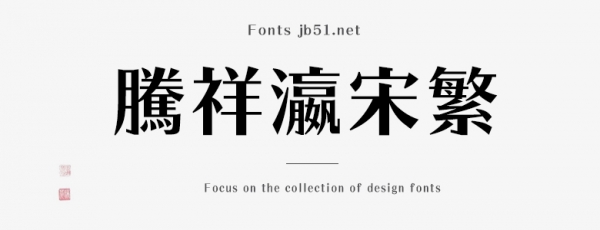
騰祥瀛宋繁-W7是一款不錯的藝術字體,由騰祥字庫出品,這款字體筆觸略顯粗實,字形端正,適合應用于藝術設計、平面宣傳設計、網(wǎng)頁設計,書法字帖等領域,需要的朋友可以前來本站下載。
此款字為騰祥瀛宋系列字庫,是騰祥公司自主精心設計開發(fā)的精品正文字庫。一共10款粗細,以期滿足用戶不同領域的用字需求。此款字為瀛宋W4,可用于正文、小標題等。整個系列字庫風格完全一致,不管是常用字或是非常用字,字字精美、結構端正、重心平穩(wěn)、美觀實用。此款字為騰祥公司推送《2019森澤字體大賽》參賽作品。